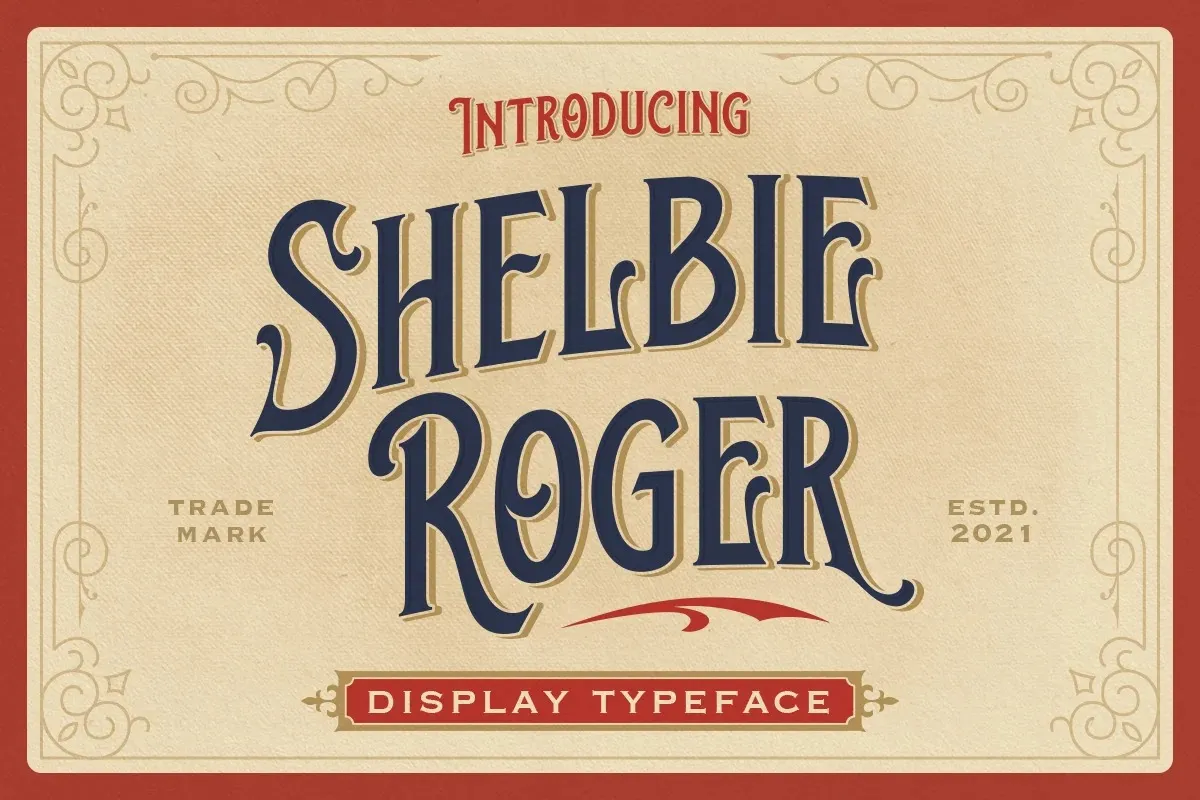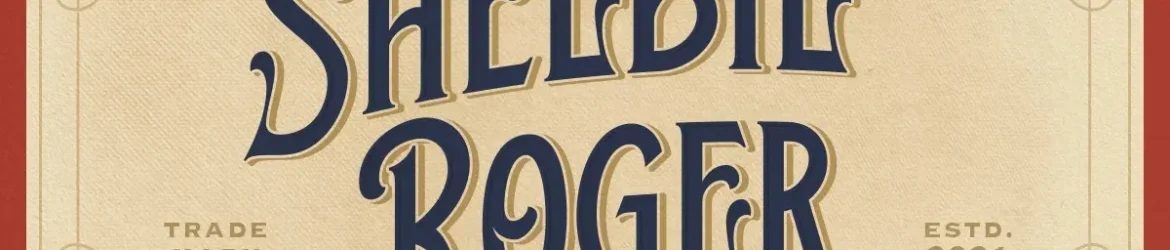
A fonte “Shelbie Roger” é uma elegante combinação do clássico e do moderno, perfeitamente adaptada para aplicações formais e criativas. Inspirada nos signings de viés dos anos 60 e 70, esta font se destaca por seu estilo único e vibrante. Perfeita para uso em logotipos, cartões de convite, embalagens, revistas ou até mesmo em cartelas de maquiagem, a Shelbie Roger é uma escolha ideal para qualquer projeto que exigir um visual moderno com toques nostálgicos. Seja você um designer criando uma marca única, ou alguém planejando uma festa incrível, essa fonte oferece o ideal entre estilo e funcionalidade. Perfectamente adaptada para diversos ambientes de marketing, a Shelbie Roger faz da linguagem visual um poderoso instrumento de comunicação.